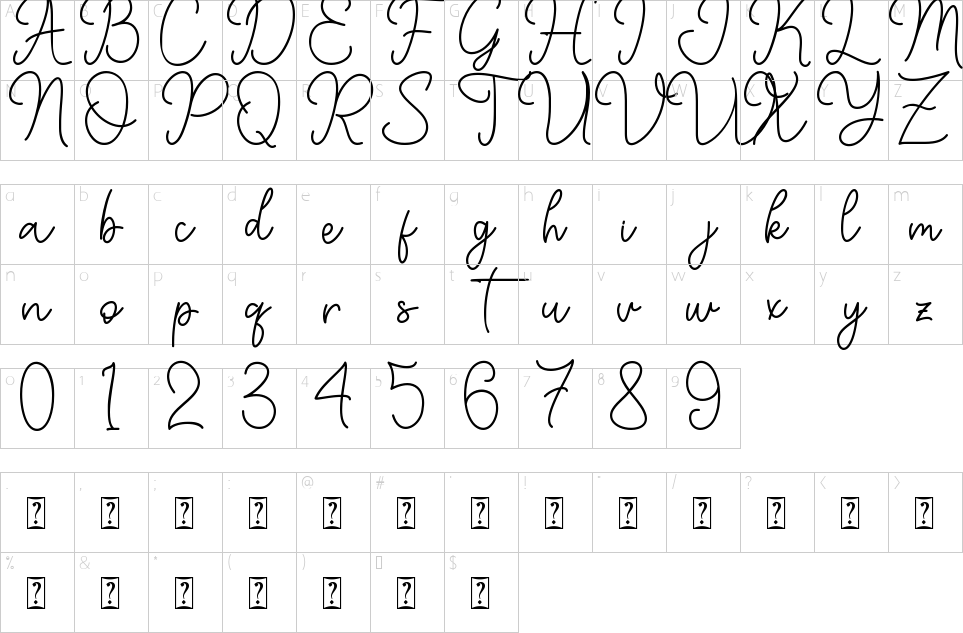
Mountline Font | 1001 Free Fonts – Fonte Grátis
A fonte Mountline é uma opção gratuita e versátil para designers e estilistas de moda, oferecendo um charme natural que combina bem em qualquer projeto. Ela foi projetada pelo designer Alif Ryan Zulfikar e é um excelente recurso para quem busca uma fonte de qualidade sem precisar pagar. Com um design elegante e um pouco moderno, a Mountline está disponível tanto para sistemas Windows quanto para Mac. Esta fonte gráfica ganhou muitos downloads, atingindo 1.491, o que mostra seu valor e popularidade. Seja para criar rótulos de produtos, design de sites ou até mesmo para adicionar um toque especial a uma publicação de redes sociais, a fonte Mountline é uma ótima escolha para tornar seu trabalho ainda mais criativo e profissional. Download agora e experimente.